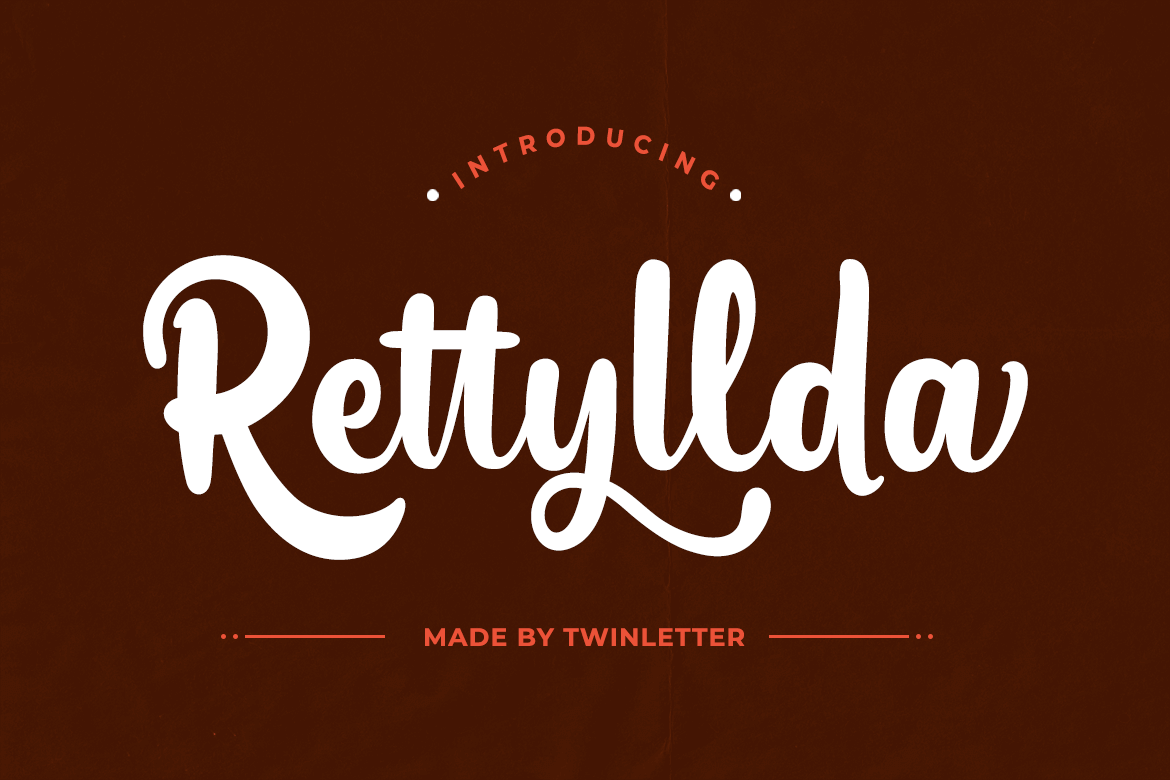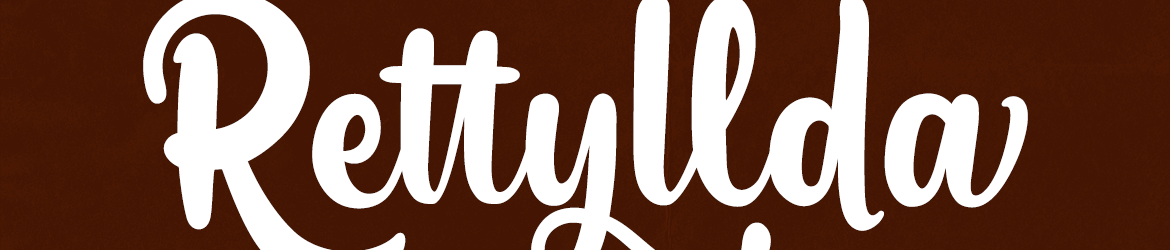
Rettyllda é uma elegante e simples fonte tipográfica em estilo script, que transmite a sensação de ser cuidadosamente elaborada por mãos humanas. Suas letras se mesclam perfeitamente, criando um equilíbrio delicado e harmonioso. Esta característica única da Rettyllda é o ligaturamento, ou sinógrafo — os conjuntos de dois ou mais caracteres que formam uma letra sólida. Este detalhe especial confere à fonte beleza e sensualidade, tornando-a uma opção perfeita para projetos criativos que desejem transmitir elegância e charme. A combinação delicada dos ligadores cria um aspecto sofisticado e poético que se adequa a vários tipos de projetos gráficos. Seja para design editorial, arte digital ou qualquer aplicação que exija uma fonte com estilo único, Rettyllda fornecerá precisão e criatividade em sua execução. Com sua simplicidade e elegância, esta font é ideal para aqueles que buscam um toque especial no seu trabalho.